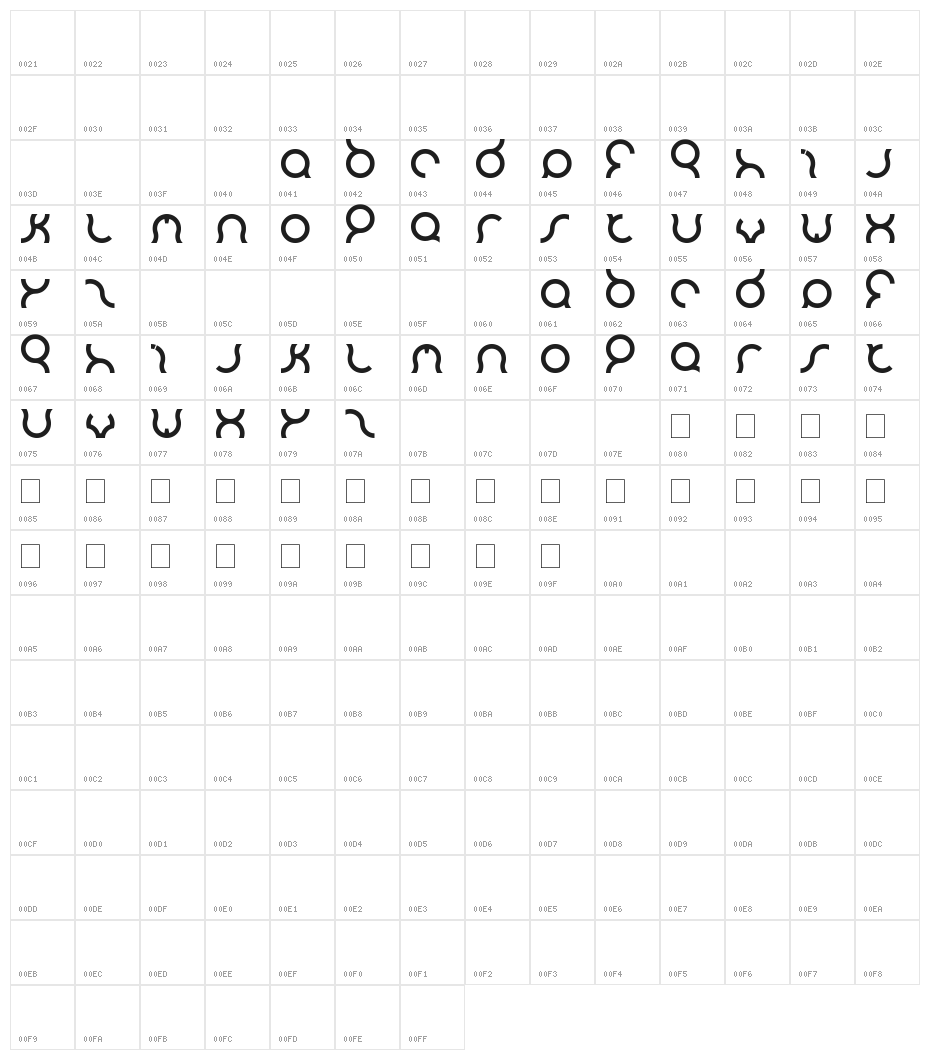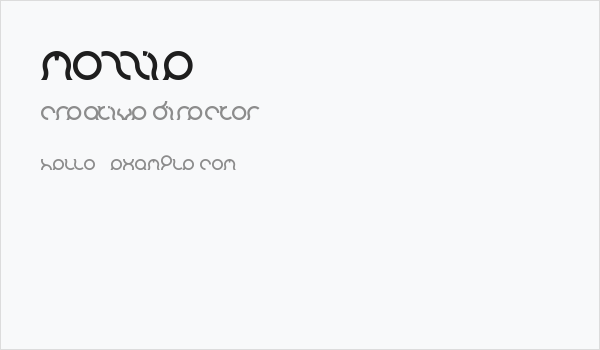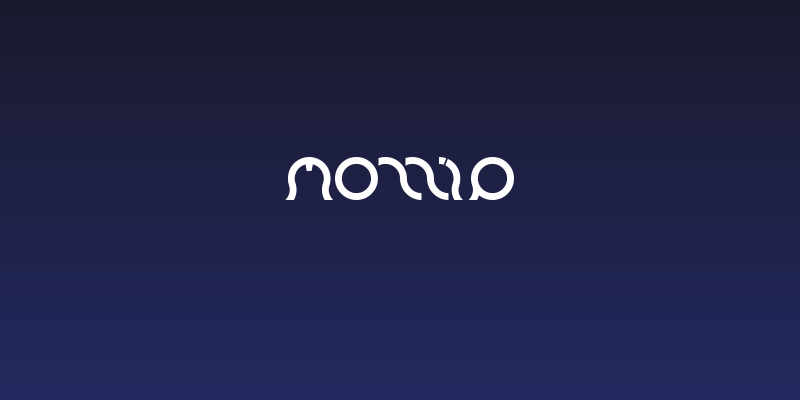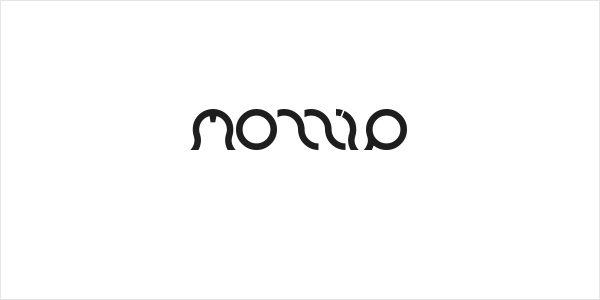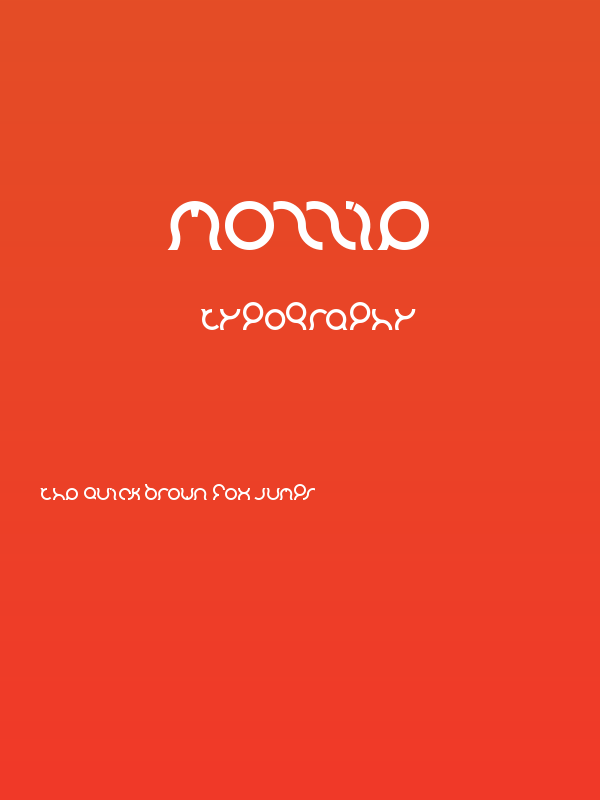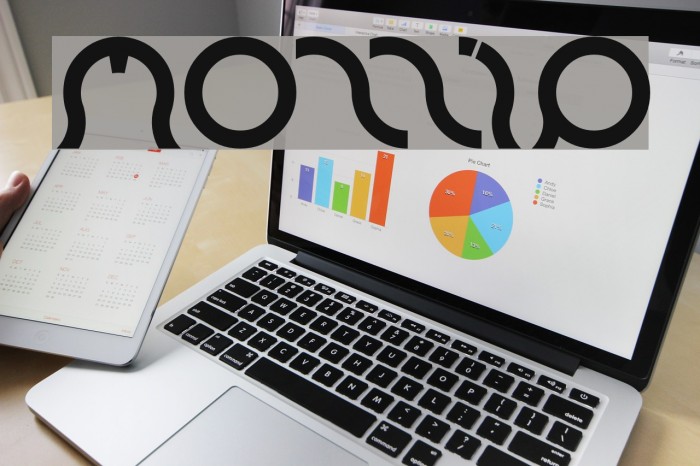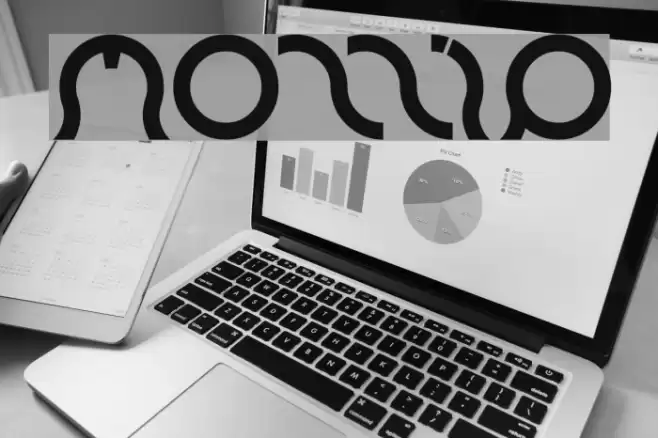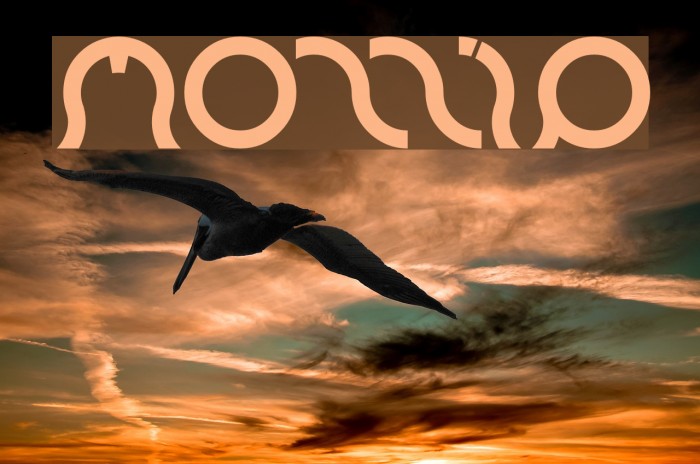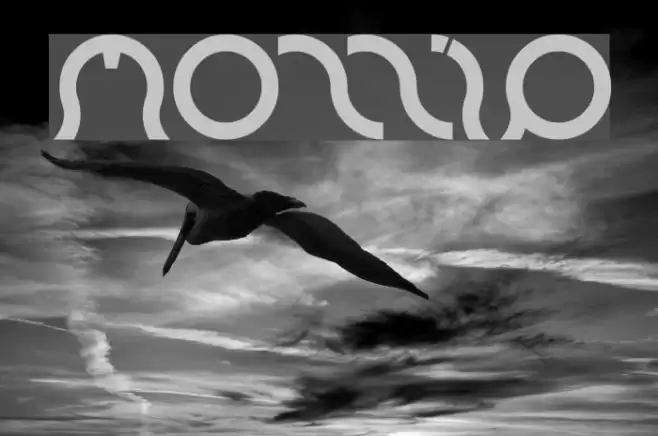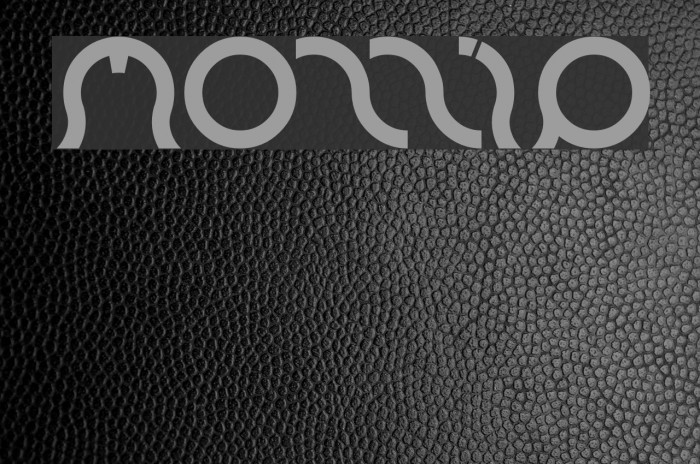
mozzie Font
| Область применения | Logos, Posters, Creative Branding |
| Рекомендуемые проекты | Ideal for creative projects such as posters, logos, and branding materials that require a distinctive and artistic touch. |